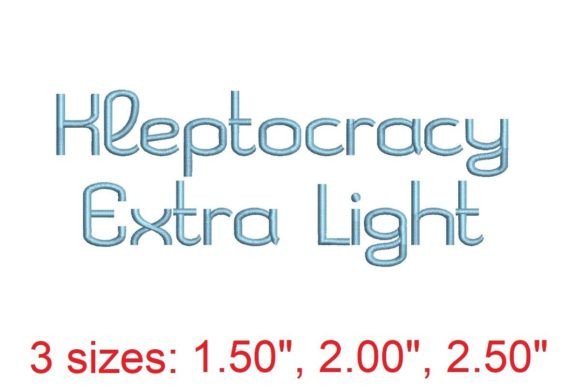
Kleptocracy EX LT Embroidery Font
Mencari elemen reka bentuk yang sesuai boleh menjadi mencabar, tetapi Kleptocracy EX LT Embroidery Font menawarkan koleksi luar biasa yang menaik taraf karya anda serta-merta.